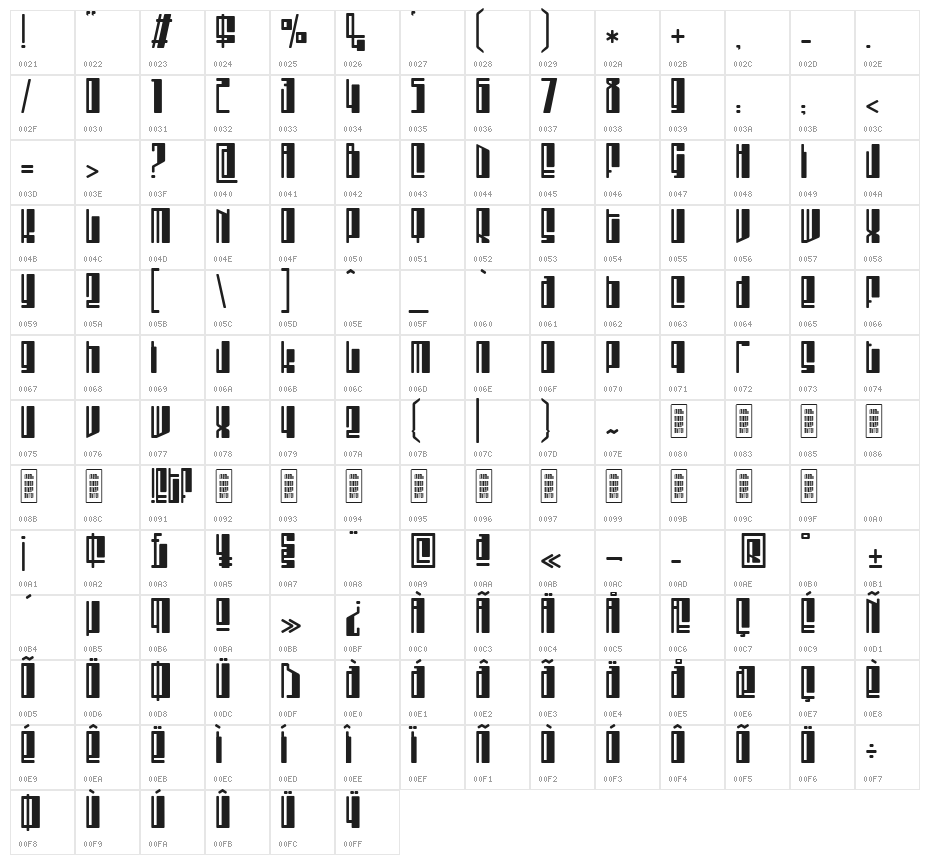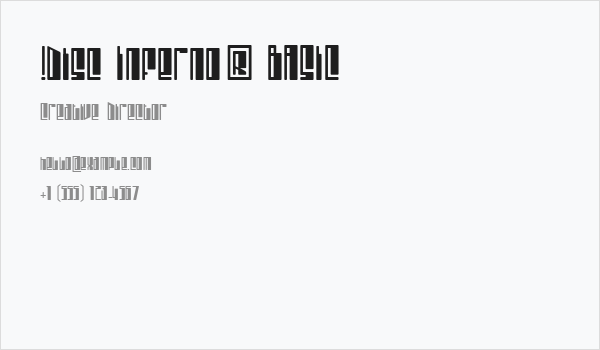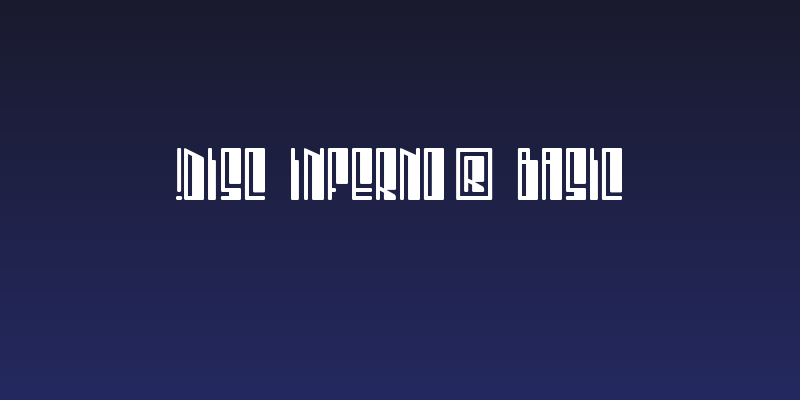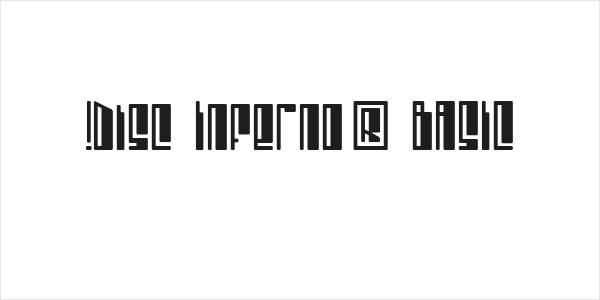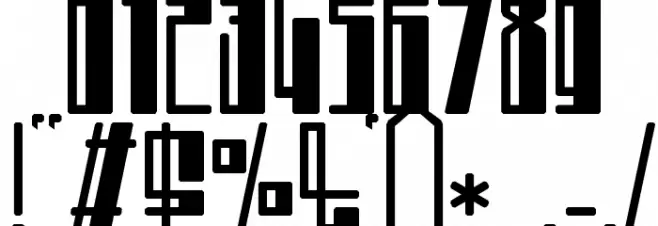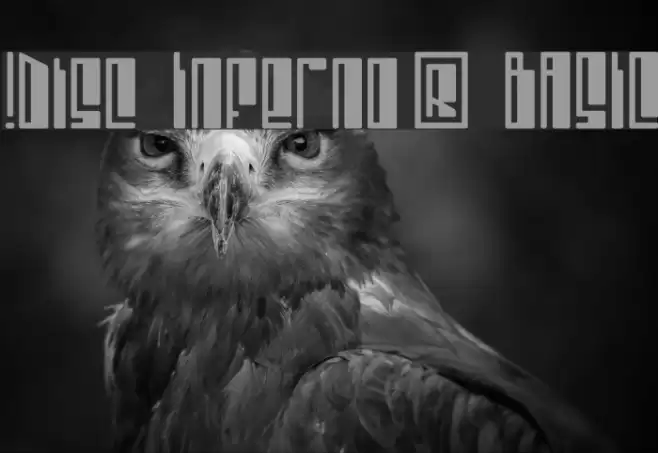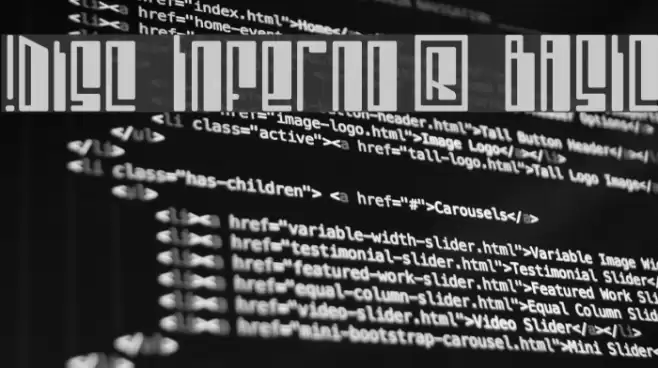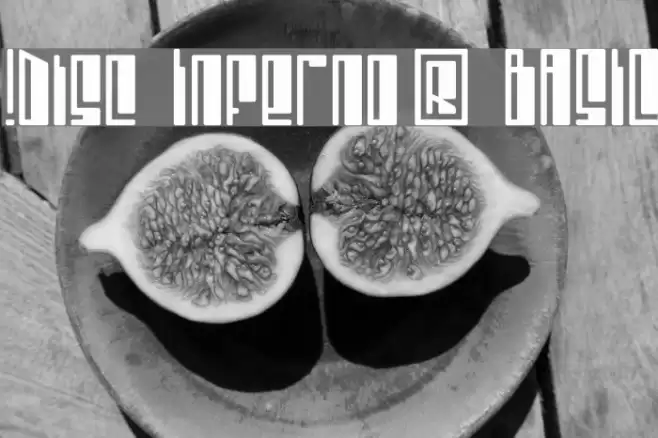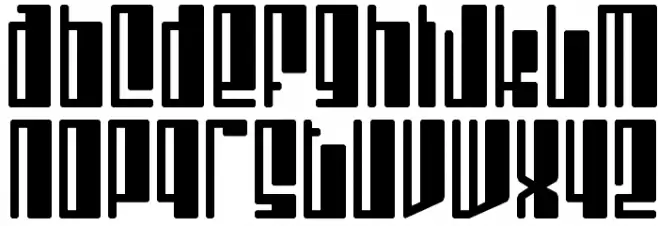
!Disc Inferno® BASIC Font
| Vorgeschlagene Projekte | Ideal for modern branding, poster design, and digital media projects where a strong visual impact is desired. |